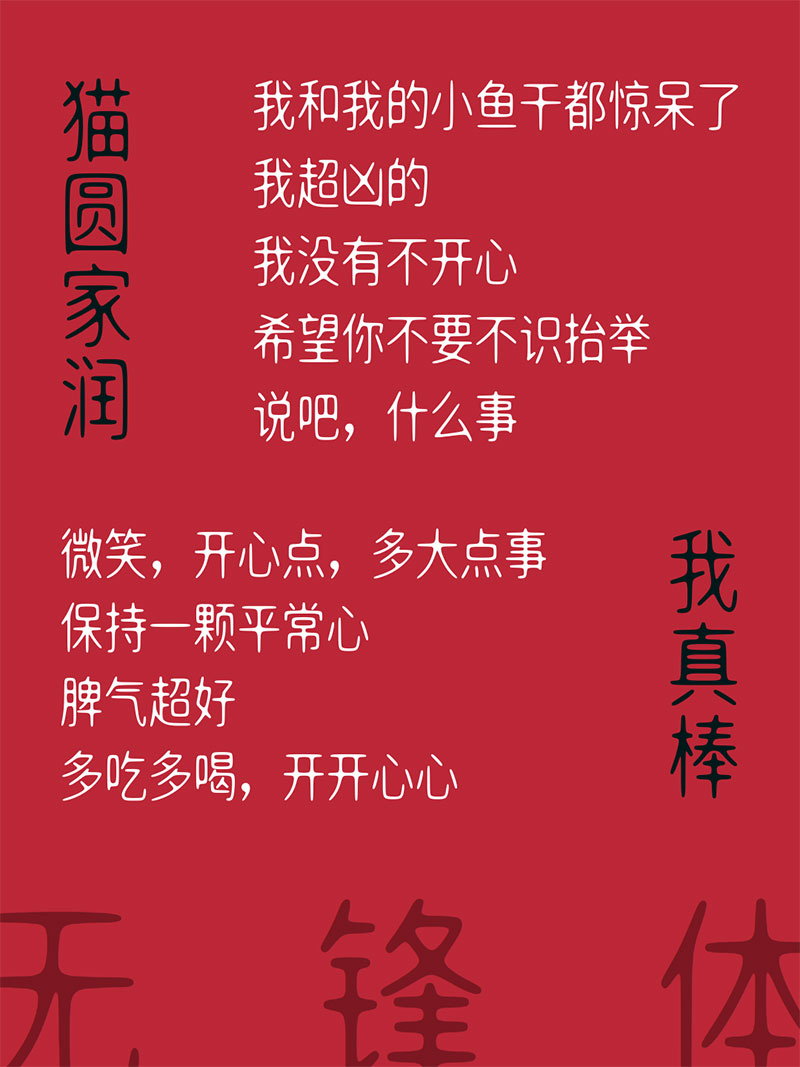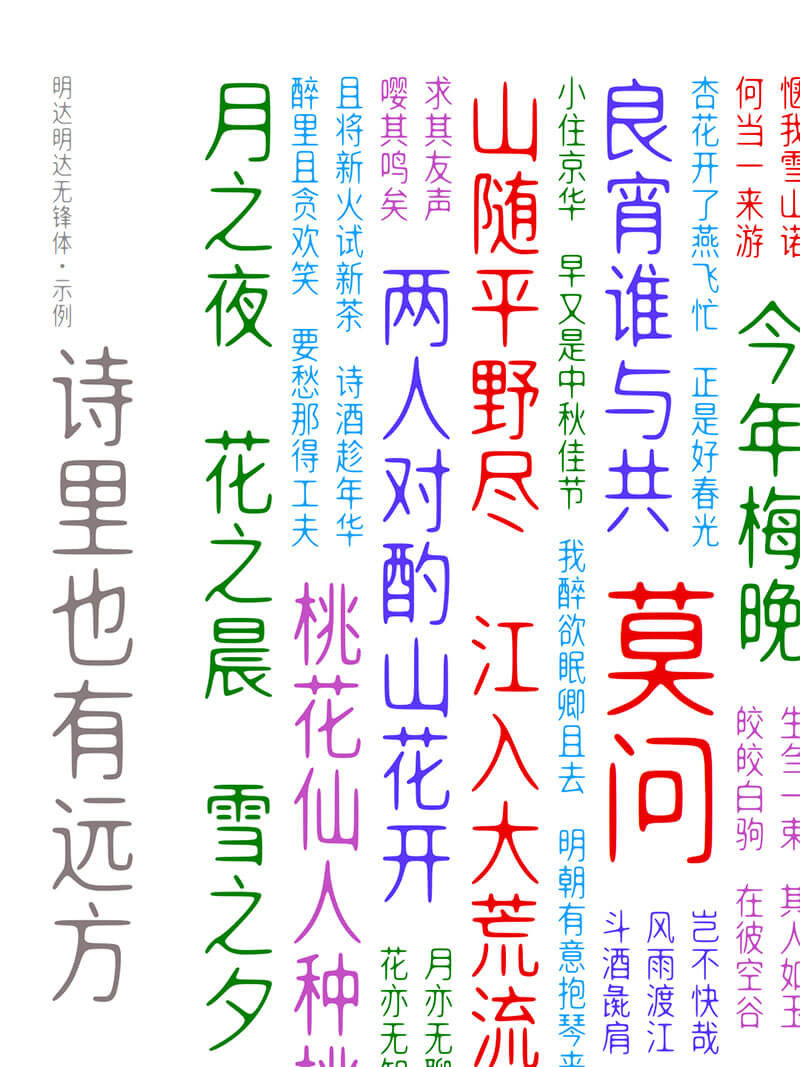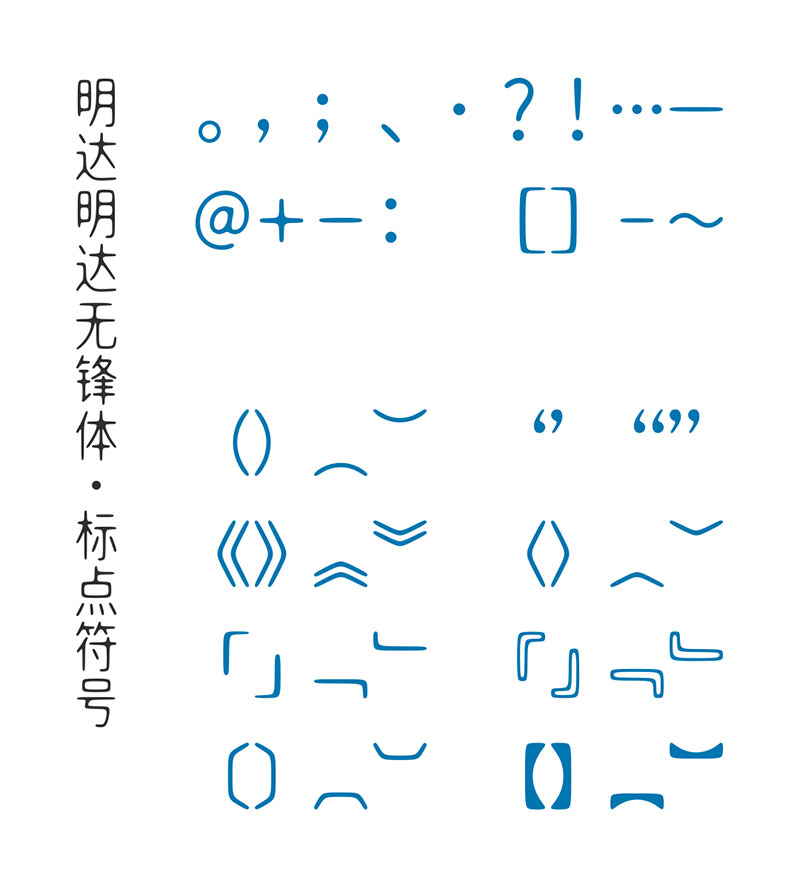
字符集合:包含GB2312中的6763個漢字和49個全角中文標點符號。(不含英文、數字)
字形特點:筆劃佈局上採用中宮放鬆的黑體佈局。在大體佈局上參考思源黑體(佈局很均勻)和以前宣傳畫的各種豎型字體,根據具體筆劃形態衝突、重心變化、美觀平衡做調整。
似水的凝聚形成“墨的無鋒”,渾圓無折角,無筆鋒,故名“無鋒體”。
字形特點:中宮放鬆,佈局舒展,步進等寬;筆劃略細,字身稍長,高:寬=5:4。